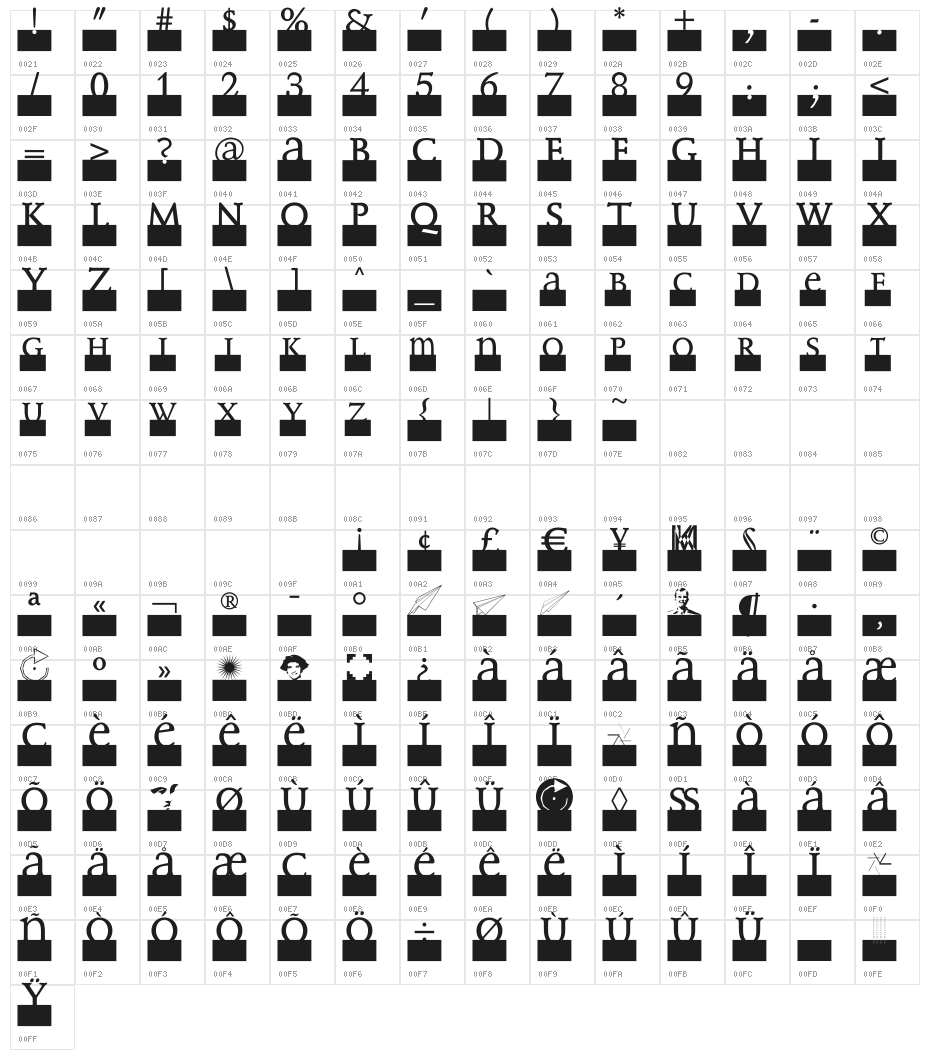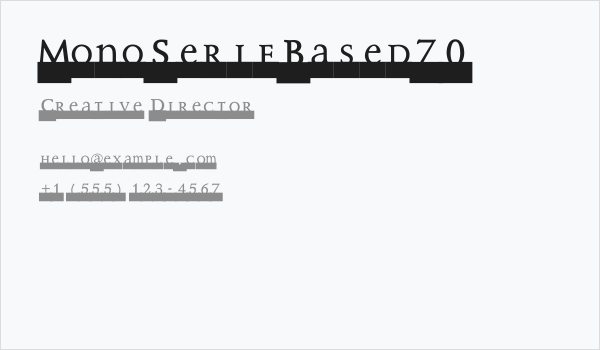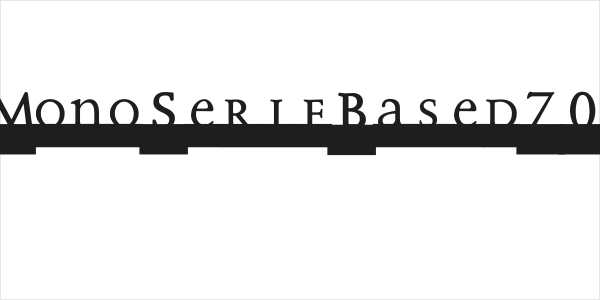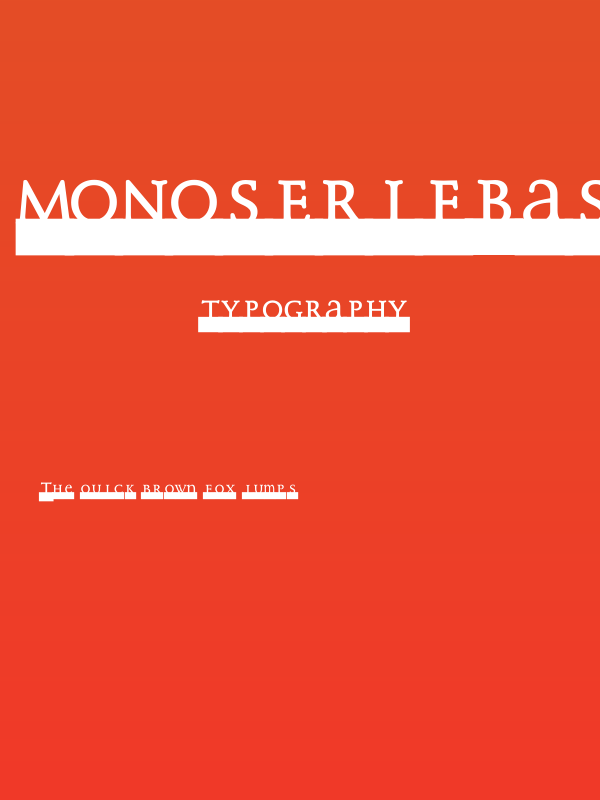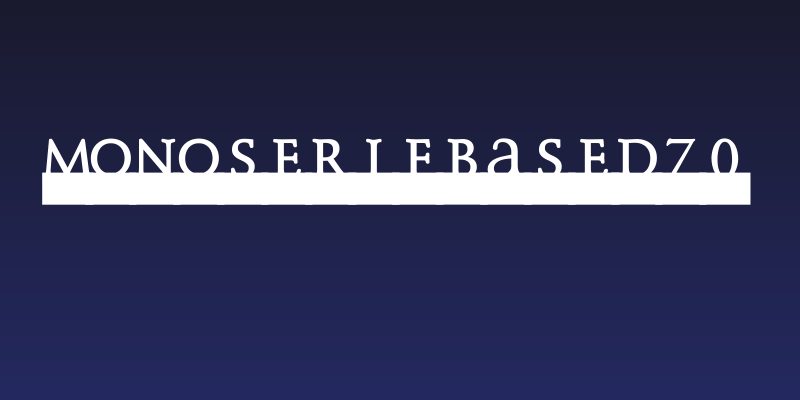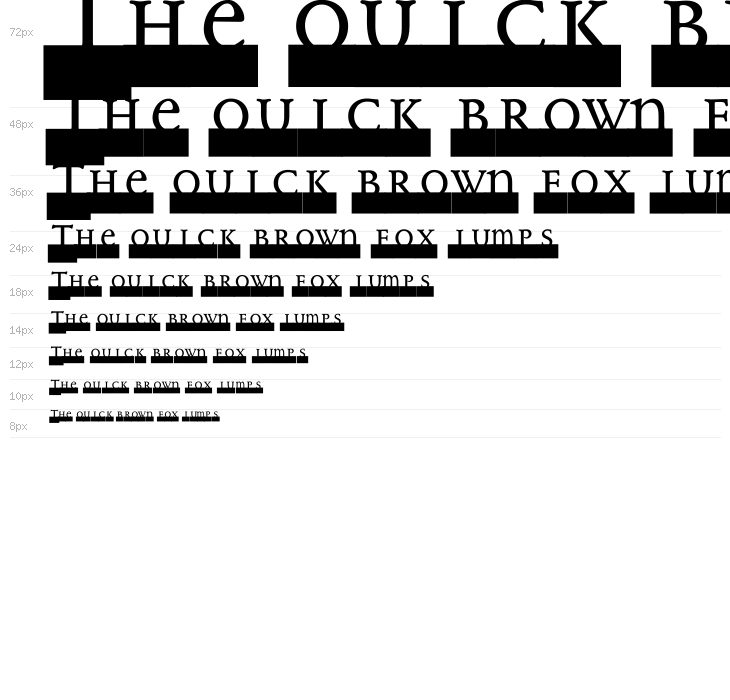
MonoSerifBased70 Font
| Gesamtstil | Classic |
| Anwendungsfall | Headlines, Body text, Logos |
| Vorgeschlagene Projekte | Ideal for formal documents, branding, editorial content, and any project requiring a professional and timeless look. |